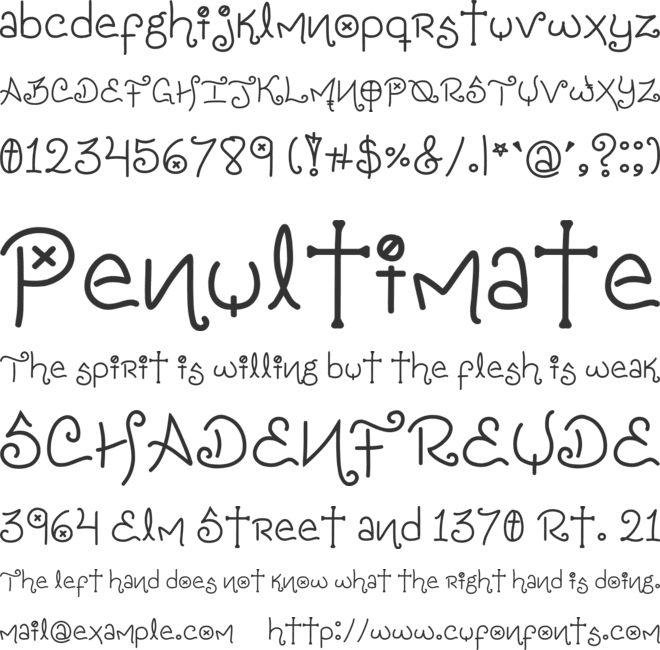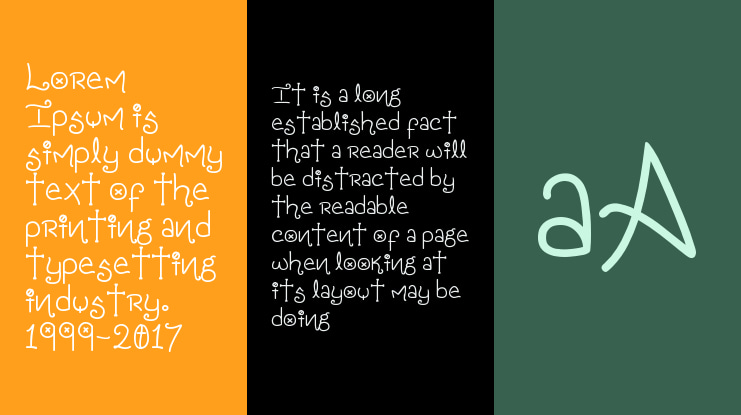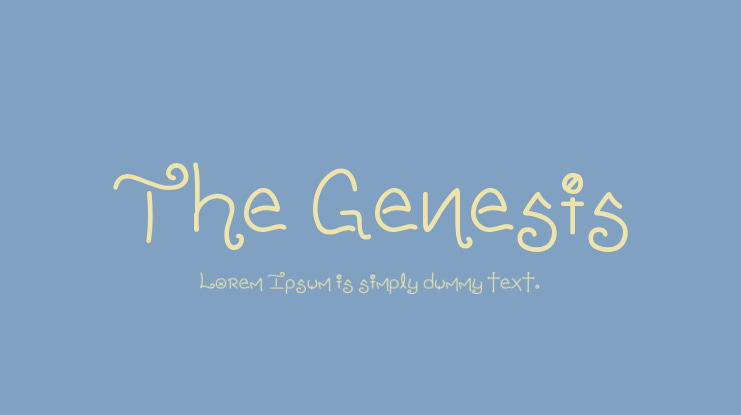
The Genesis Font
Génesis Toxical
Esta font se basa en mi tipo de letra al escribir títulos. Con este signo "☺" puedes sustituir la -o- minúscula con una calavera, la araña es "" y la calavera grande es "○".
Génesis Toxical ( 2017-2019 )